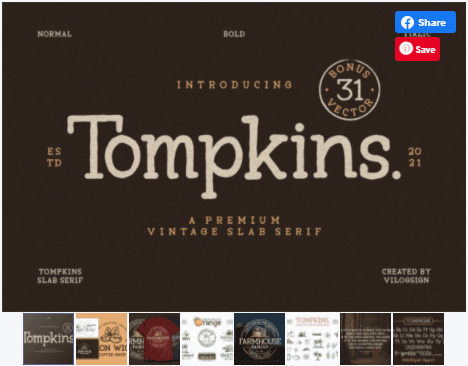
Tompkins Font
Tompkins - замечательный винтажный шрифт с засечками, который выглядит одновременно поэтично и торжественно. Он станет отличным дополнением к вашей библиотеке шрифтов, так как может улучшить внешний вид любого творения!